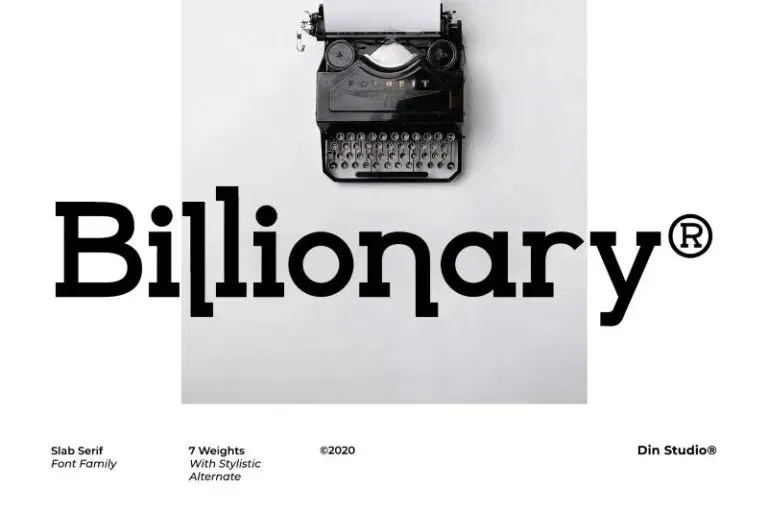
A Billionary Font é uma escolha perfeita para quem busca uma mistura única entre a modernidade e os clássicos do tipo serif quadrado. Com esta família de tipos, você terá muitas opções para capturar, envolver e inspirar seus ouvintes e clientes. Esta fonte é ideal para várias necessidades de conteúdo, projetos impressos e digitais. Perfeito tanto para as necessidades específicas de redes sociais como em designs fashion, também funciona perfeitamente com slogans impressos, embalagens e até mesmo como um overlay estiloso do texto sobre qualquer imagem de fundo. Composta por Din Studio, a Billionary é uma opção ideal não só para projetos modernos, mas também para aqueles que desejam uma pegada mais clássica em seus materiais. Não perca essa oportunidade de dar um toque especial ao seu design com esta fonte incrível e versátil.